包装届“最卷”的咖啡如何设计突围?
近年来,国内咖啡作为新兴赛道,品牌数量随着市场需求量激增,毫不夸张地说,咖啡几乎是所有新消费品类中最“卷”的一类。与此同时,咖啡文化逐渐渗透年轻人日常生活的方方面,这意味着咖啡正从办公室、CBD等场景配角转变为消费主角,甚至成为了消费者表达的个性与自我的一扇窗口。
咖啡角色的身份发生转变,各咖啡品牌开始越来越注重视觉形象。一套完整的视觉系统或许能“圈”住部分年轻消费者,但他们依然需要大大小小的触点来感知品牌内涵的精神和理念,进而决定是否要继续选择这个品牌。咖啡包装不仅对美观性有一定要求,还要求在储存、保鲜等功能性达到一定标准。因此,除了打造新鲜的视觉感受,咖啡产品包装设计的创新,更是品牌突围的关键之一。
本篇中,Design360°收集、整理了国内外共15个咖啡品牌/产品平面视觉及产品包装设计,这些品牌战略各有侧重,在视觉上也呈现出不一样的风格调性,一同来感受咖啡视觉场景的多样性吧。
(01)
AOKKA
lowkey design
融入户外元素的多元咖啡品牌
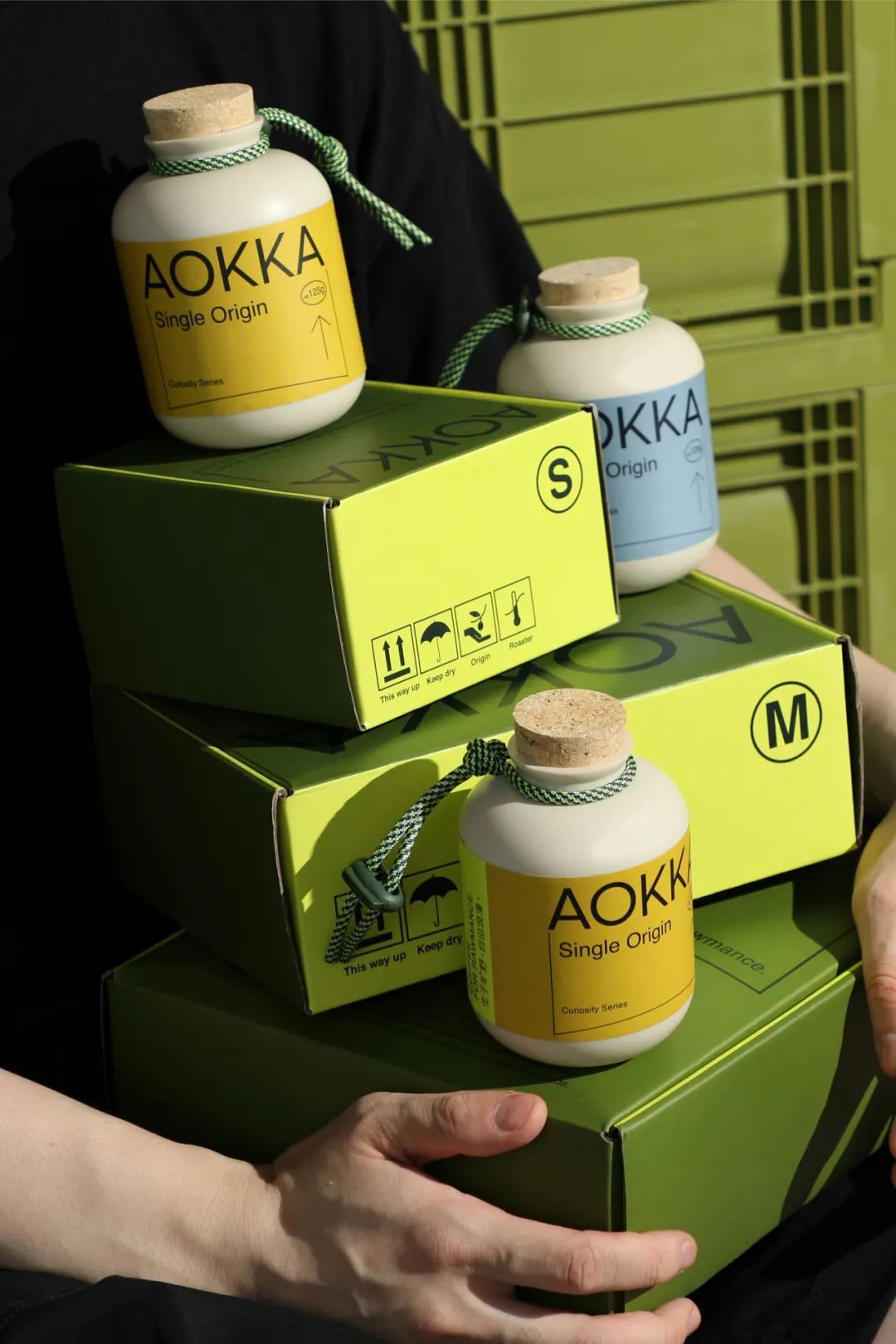
AOKKA品牌主理人Robin是一位热爱咖啡、热衷于户外与记录的实干家。因应主理人的追求与态度,AOKKA被赋予了“独立和自由”的品牌精神,以及“荒野俱乐部”的品牌概念。设计师将这一特征放大,并将旷野、公路指向标、帐篷、地平线等元素提炼、总结,以此为概念转化成辅助LOGO。
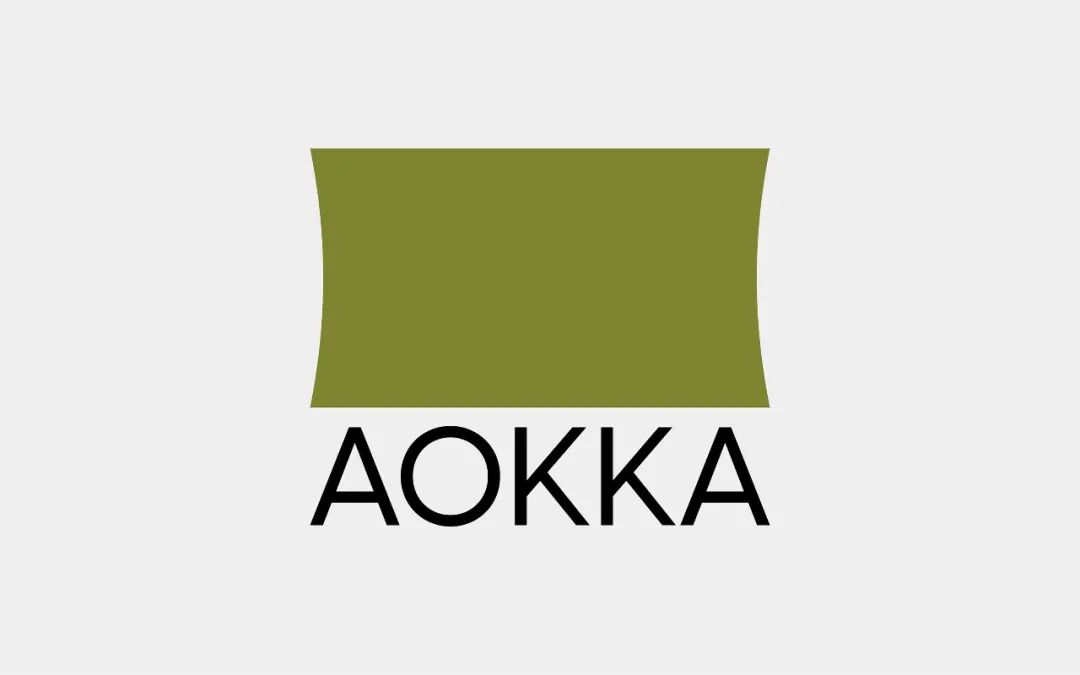
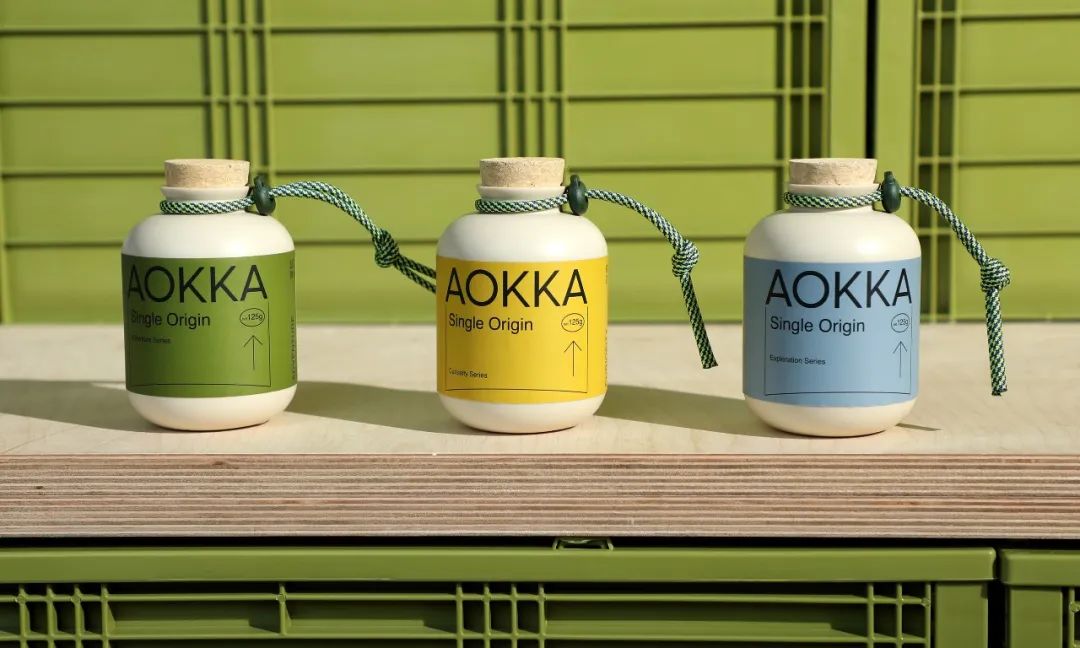
在产品设计和包装视觉上,AOKKA同样遵循着这样的品牌理念。品牌主色为绿色和荧光黄,绿色属于荒野的颜色;荧光黄的灵感则源于户外产品和运输安全的标识。产品包装灵感源于户外机能物件,经典的咖啡豆罐用到了软木塞;咖啡豆袋用到了户外伞绳、锁鲜自封条等;意式铁皮马口铁罐豆罐则借鉴了能量储备桶的造型,具有十分强烈的户外属性。
咖啡杯是一家咖啡店的灵魂。行李标签吊牌作为品牌视觉元素之一,设计团队将这个概念延续到咖啡杯的设计中,寓意每一杯咖啡都拥有标签。
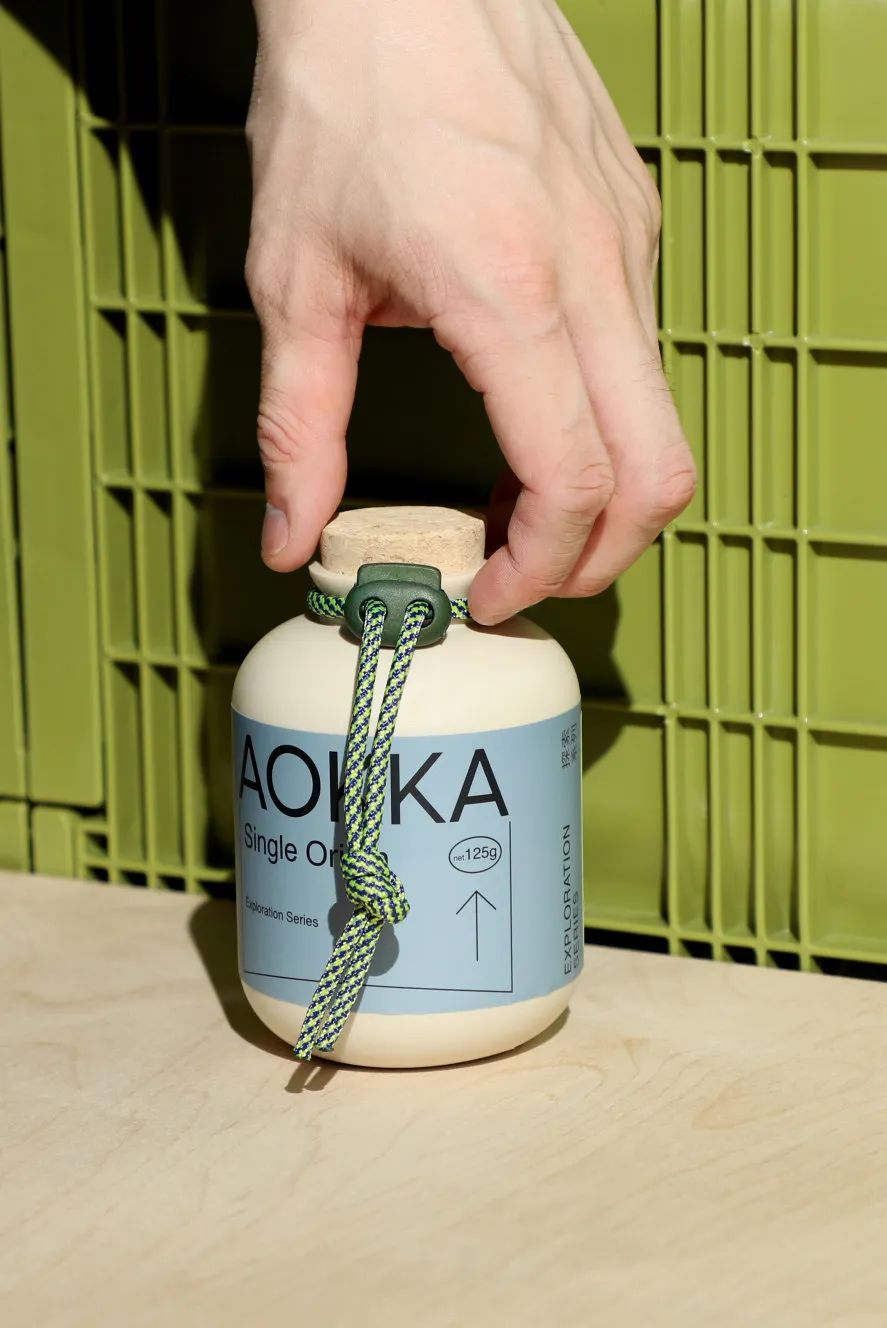
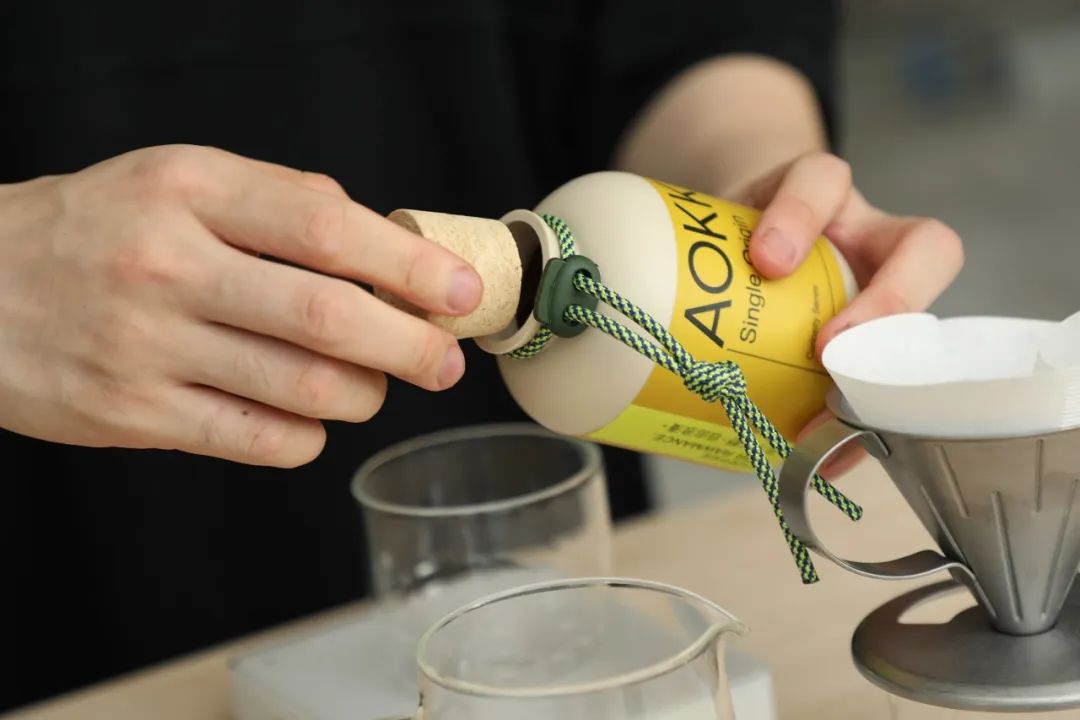
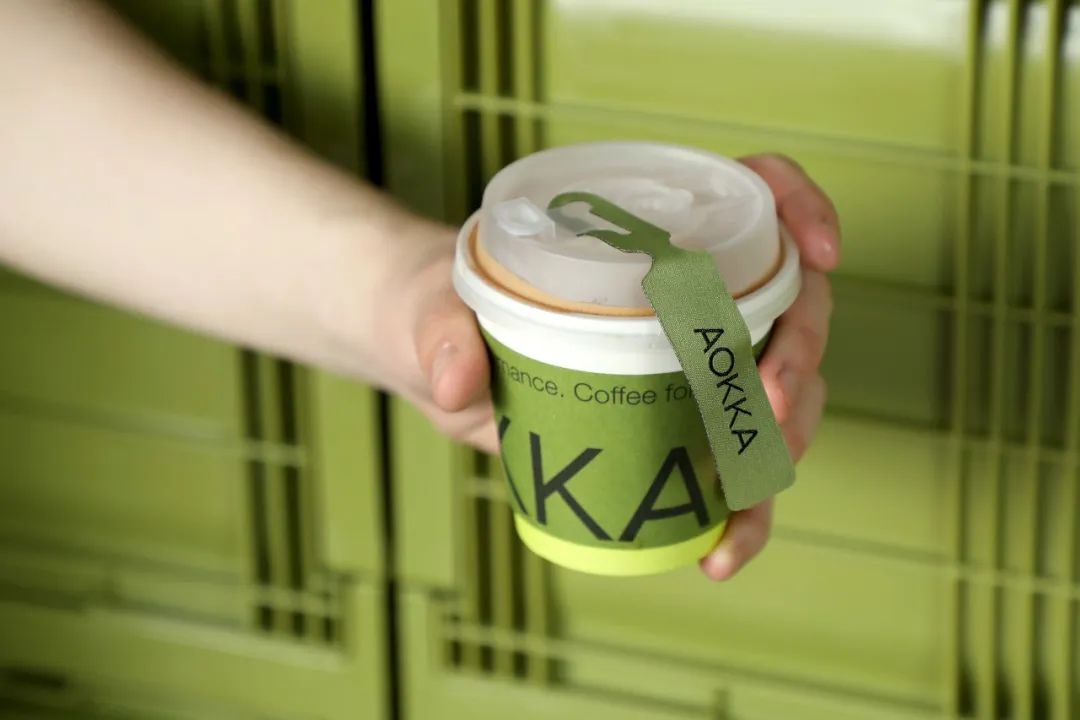
(02)
Aroma coffee
整点彩蛋 SURPRISE
主打“嗅觉先行”的独立咖啡品牌
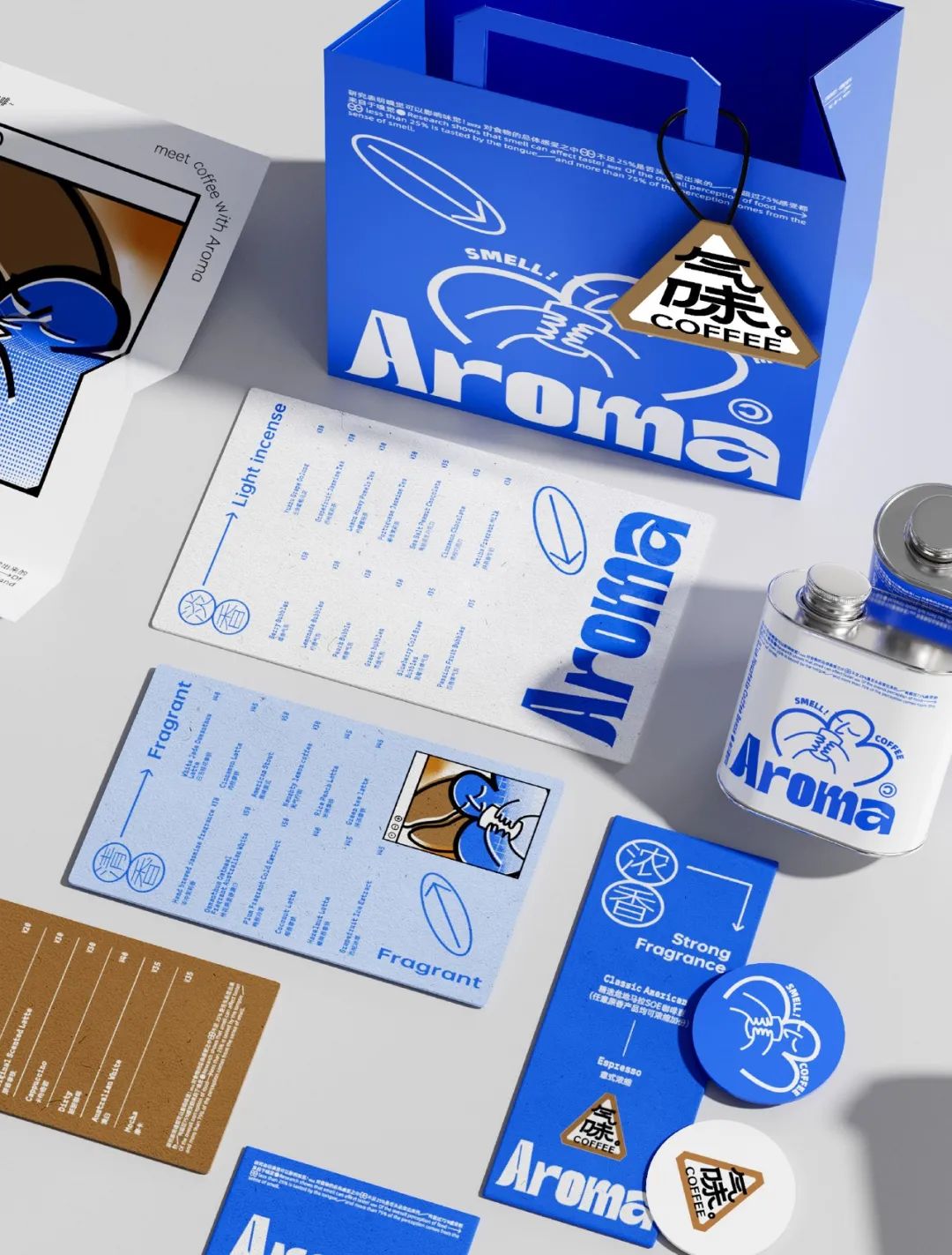
Aroma是一家来自苏州的独立咖啡品牌,旨在向消费者传递“用气味遇见咖啡”的理念。为了与市面上众多咖啡品牌区分开来,Aroma以“嗅觉先行”为宗旨,强调咖啡的多样化体验。
因此,在视觉呈现上,设计团队围绕着“气味、感性、嗅觉”这三个关键词展开联想,结合产品类型,将咖啡的香气分为四个等级进行可视化设计。
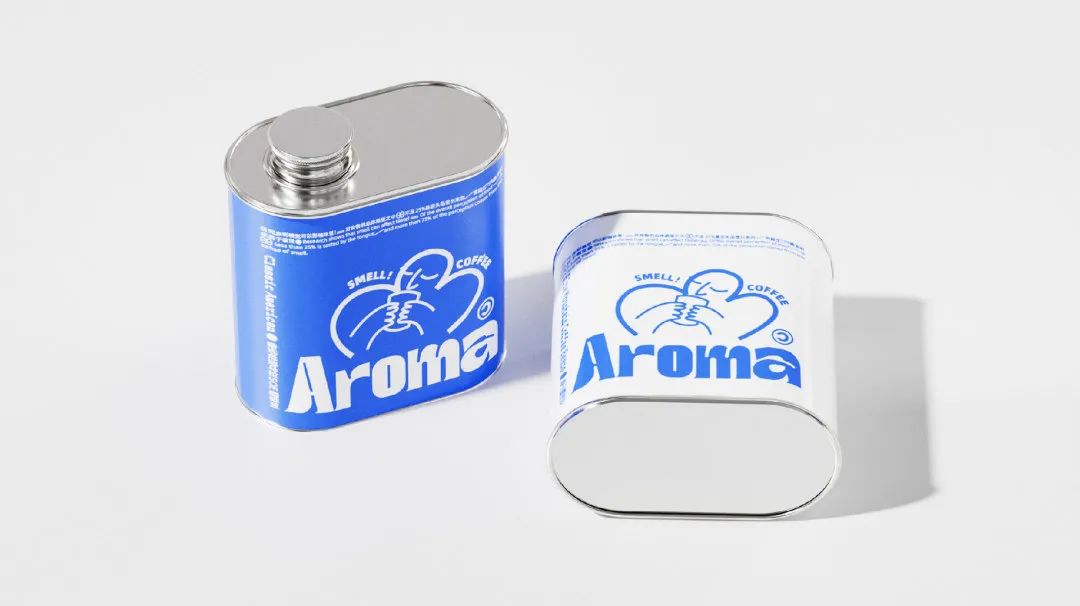
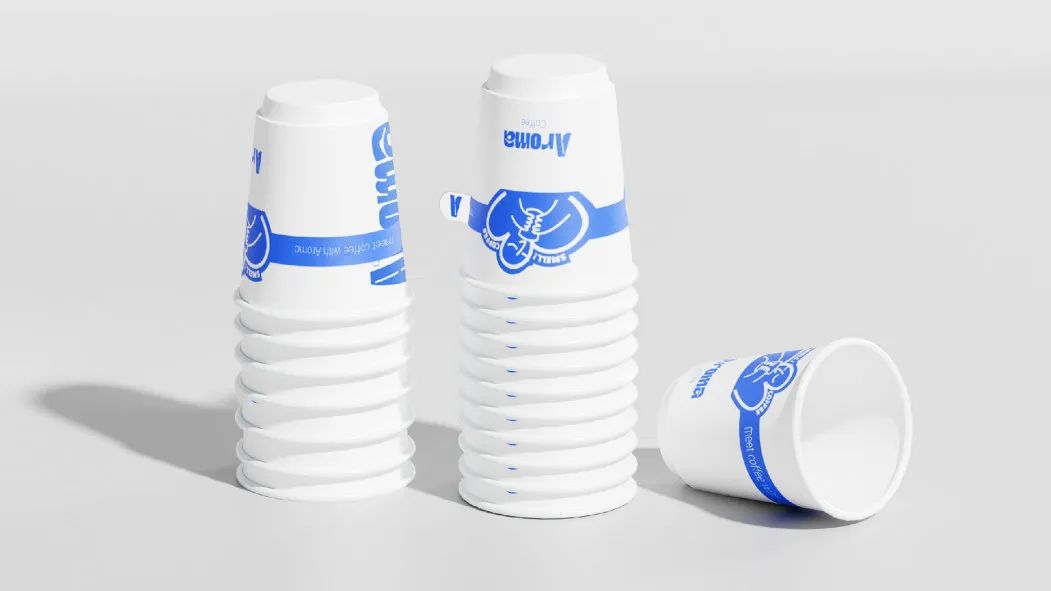
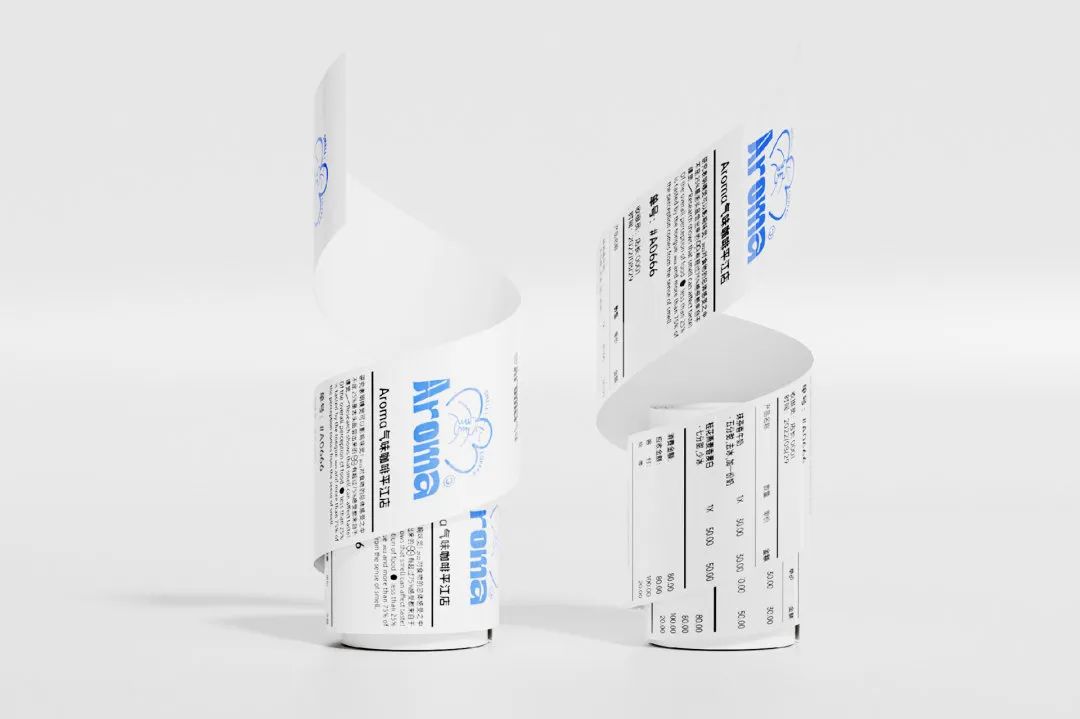
(03)
BREAD&PEACE
想象之外品牌设计
蓝色是品牌精神表达,也是对咖啡“乌托邦”的追求
BREAD&PEACE 品牌名源于《列宁全集》在书中,“面包”与“和平”是贴近社会主义的前阶象征着一种对实现社会主义的理想与追求,这也是主理人对希望经营好店铺的期望。在设计上,想象之外品牌设计跳脱常规烘培和咖啡品牌风格,选用明快高饱和的蓝色作为主色调,给人一种宁静、和谐的深刻视觉感受。
(04)
Coffeeology
makkaihang design
将“咖啡学”符号化,简约不失活泼
作为广州新兴的咖啡烘焙连锁,“Coffeeology 咖啡学”专门为广州的咖啡爱好者挑选和检测精致的咖啡和原料。Coffeeology的LOGO由俯视的咖啡杯形状转变而来,放大了顾客与品牌之间的关联,结合生动大胆的色彩。COFFEEOLOGY中选取“OLO”英文字用作性格鲜明的形象IP。
(05)
CUBIC3 三立方
lowkey design
以极简设计呈现咖啡连锁店视觉
CUBIC3 三立方咖啡是lowkey design在2021年收到的委托,基于希望提供平价、高品质的咖啡的品牌定位与密集分布于社区与商业区的拓店计划为背景,设计一套更简约、质感与高传播性的品牌视觉。
三立方以(m)³作为LOGO符号,low low team提出“以小建大”的设计概念,象征每一个独立的个体。因此,外包装被设计成一只只小的立方体,并收纳于大份礼盒中,表达“立方集聚,包容万象”的内涵。
品牌的材质设计以极简的视觉呈现。而品牌的主视觉则是品牌蓝色与CUBIC3 LOGO相组合。作为一个以平价为特色的咖啡连锁品牌,CUBIC3专注于制作经典咖啡,一杯美式自带杯只需5元。实惠的价格但设计却是精致,lowkey design为其设计了包括手握纸杯、塑料杯、随行杯等不同杯型。
除此之外,low low team将CUBIC3的周边设计命名为“3 Colletion”。数字“3”本身具有美好的寓意,即“3生万物”。
(06)
COLON COFFEE ROASTERS
paragram
以“时刻”为视觉中心的打工人咖啡豆包装
“colon coffee roasters”名称源于用来显示时间的“冒号”符号。正如品牌的用户定位,这是一款为办公室打工人而生的咖啡品牌,即根据适合消费者的工作方式和生活方式的“饮用时间”,选择合适的咖啡豆。
“colon coffee roasters”有四款经典包装款式。“9:00”意为平衡、永恒,适合早餐饮用;“12:30”是清爽的风味,咖啡因含量高,适合午后饮用;“15:00”适合与甜食牛奶搭配,可释放精神疲劳;“22:00”是无咖啡因款,睡前喝也能安然入睡。
(07)
KEW 3101 Coffee
LHCK-Brand
点、线、面的包装视觉延展
KEW 3101是一个专注咖啡口感平衡的咖啡文化品牌,2020年成立于厦门。在2022年的品牌更新中,设计团队LHCK-Brand提取了品牌“严谨”“秩序”“平衡”的咖啡理念,结合品牌门店“点、线、面”的秩序美学,展开一系列视觉呈现。
(08)
le brewlife 乐步
lowkey design
以“胶卷旅店”为灵感,打造别致的咖啡外包装
le brewlife乐步咖啡是一个新潮、时髦趣味、充满仪式感及倡导“乐步人生”的独立咖啡品牌。“乐”寓意享受生活非凡却平凡的每一个瞬间,比如喝一杯咖啡、看一场日落的浪漫平凡日常,“步”代表着行走于纪录,心中饱有生活的火花,所以不断探索发现,正如le brewlife品牌SLOGAN对生活与人生简单有力的表达:“Spark the moment / 点燃发光时刻”。
设计团队用“胶卷旅店”为设计意向,来表达乐步咖啡对平凡生活始终饱有的热情,心中有火花,世界才有涟漪。旅途中会使用到的胶卷相机,是记录与发现美好的瞬间的图像工具,旅店是行走路途中的休息站,是放松与享受。于是,胶卷筒、行李吊牌、扎带等等都成为表达乐步咖啡品牌理念的视觉元素。
常温浓缩咖啡液是在旅途中最方便快捷的方式享用到一杯好咖啡,它同时作为乐步咖啡核心产品之一,low low team将胶卷筒融入到外包装的设计中,被影相光谱激发灵感,以城市为名,以旅行为乐,创造了三款城市渐变光谱。
(09)
Letter Coffee
张韬zhangtao
以咖啡烘焙程度做产品视觉区分
Letter 咖啡以品牌名字为基础,此形象延展设计了不同风格的字母,配合专业的调色板,表现咖啡不同的烘焙度及口味。Letter根据咖啡烘焙程度做产品视觉上的区分,具有艺术、抽象感的字母在冷色调的品牌上更显出挑,不免让人好奇其中的咖啡风味。盒装采用了镂空形式,内置胶囊咖啡,显得别致又趣味。
(10)
能喝的文库本
田中せり
将阅读感受口味化,风味由人工智能决定
日本设计师田中せり为NEC和咖啡店的共同企划——“能喝的文库本”(飲める文庫)设计了一系列海报和咖啡包装,包括咖啡豆袋和挂耳咖啡。涉及的经典文学作品有夏目漱石的《我是猫》、太宰治的《人间失格》、森鸥外的《舞姬》等。有趣的是,这些作品的咖啡风味都是由阅读了过万篇读后感的人工智能AI决定的。
阅读经典文学作品会激发一系列复杂的情绪,可以描述为甜、苦或刺激——这些词也被用来描述食物和饮料的味道。例如夏目漱石的《心(こころ)》,讲述了一个被困在过去的男人的故事,他为爱背叛了朋友而感到内疚。
而这款拼配咖啡豆产地来自印度尼西亚、巴西、危地马拉,选用意大利烘培。来自印尼的曼特宁,加上巴西的尖锐苦味,酒体丰富,质感高。深沉的丰盈和饱满的肉体,让人窥见潜藏在每个人心中、危难时现身的苦涩人性。
(11)
ORA coffee
indego design
用不同的字体,打造品牌AB面个性
ORA Coffee作为澳门知名的青年文化聚集地,特别注重空间与人的关系,以及对精神生活的各种思考。三种不同颜色的立方体代表 ORA、空间和人。indego design选择了两种完全不同的字体来打造品牌的个性。方形结构的字体代表了空间中人与人之间的关系,活泼的字体代表了人们对生活的热爱。
(12)